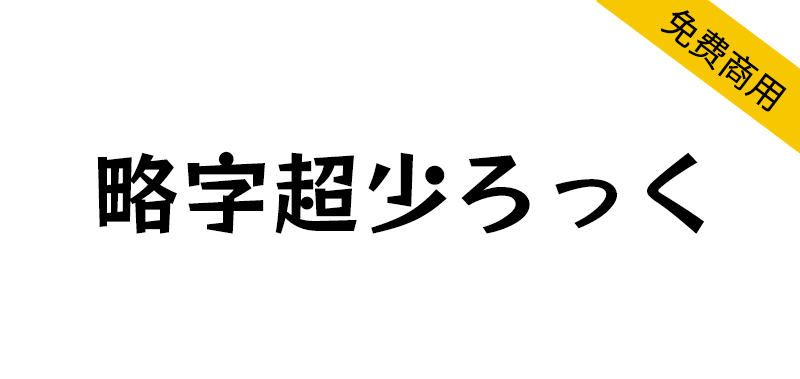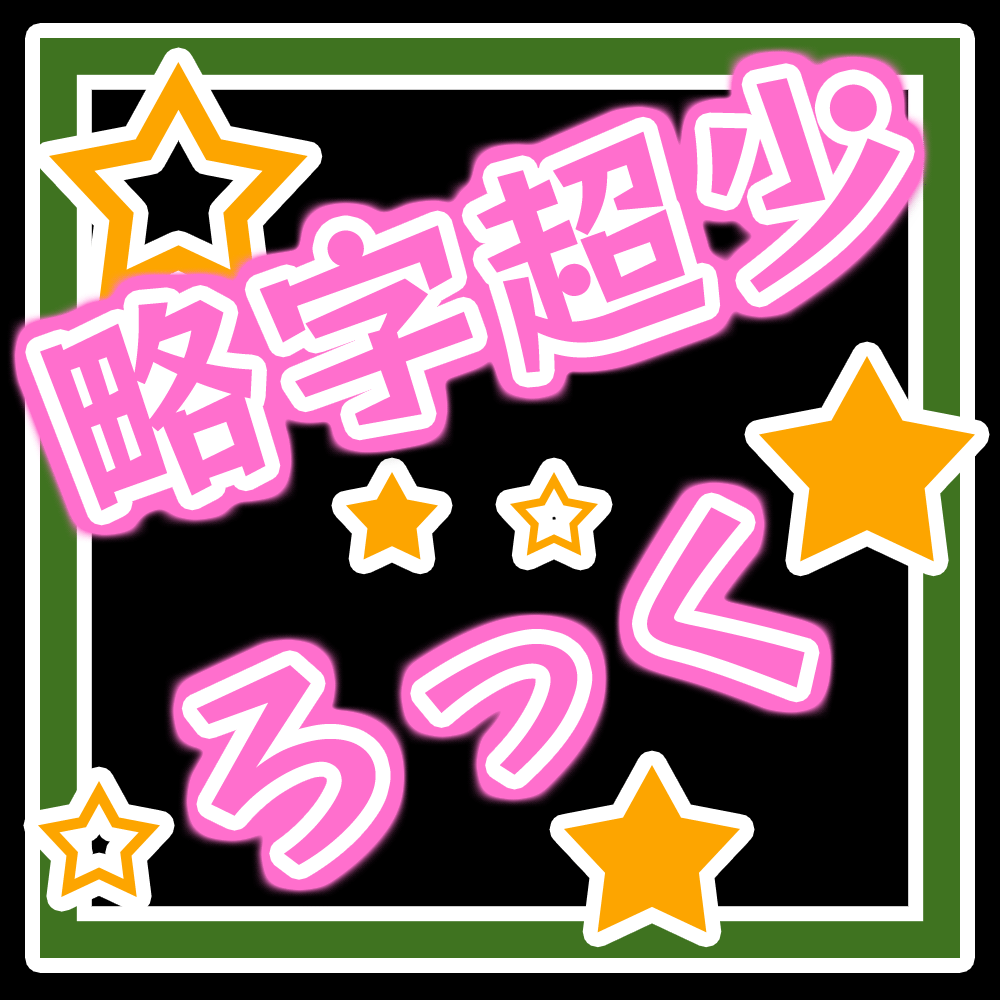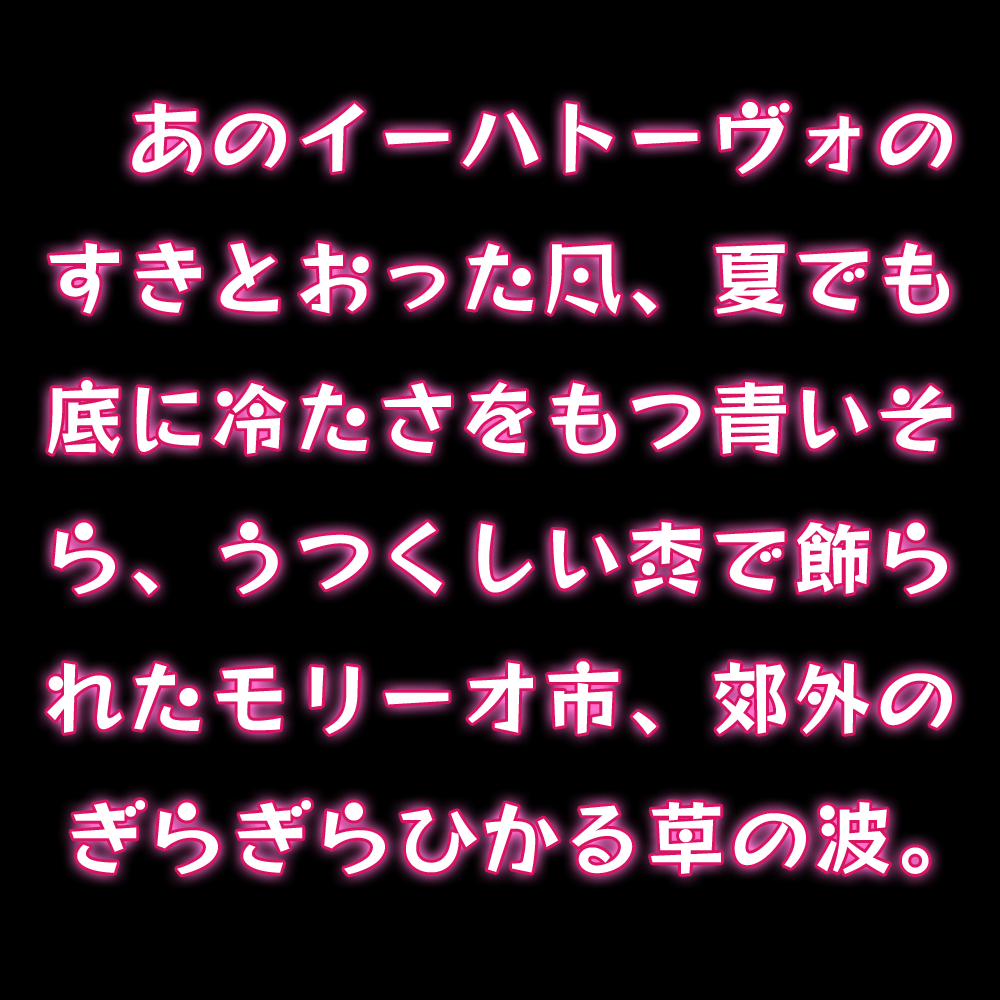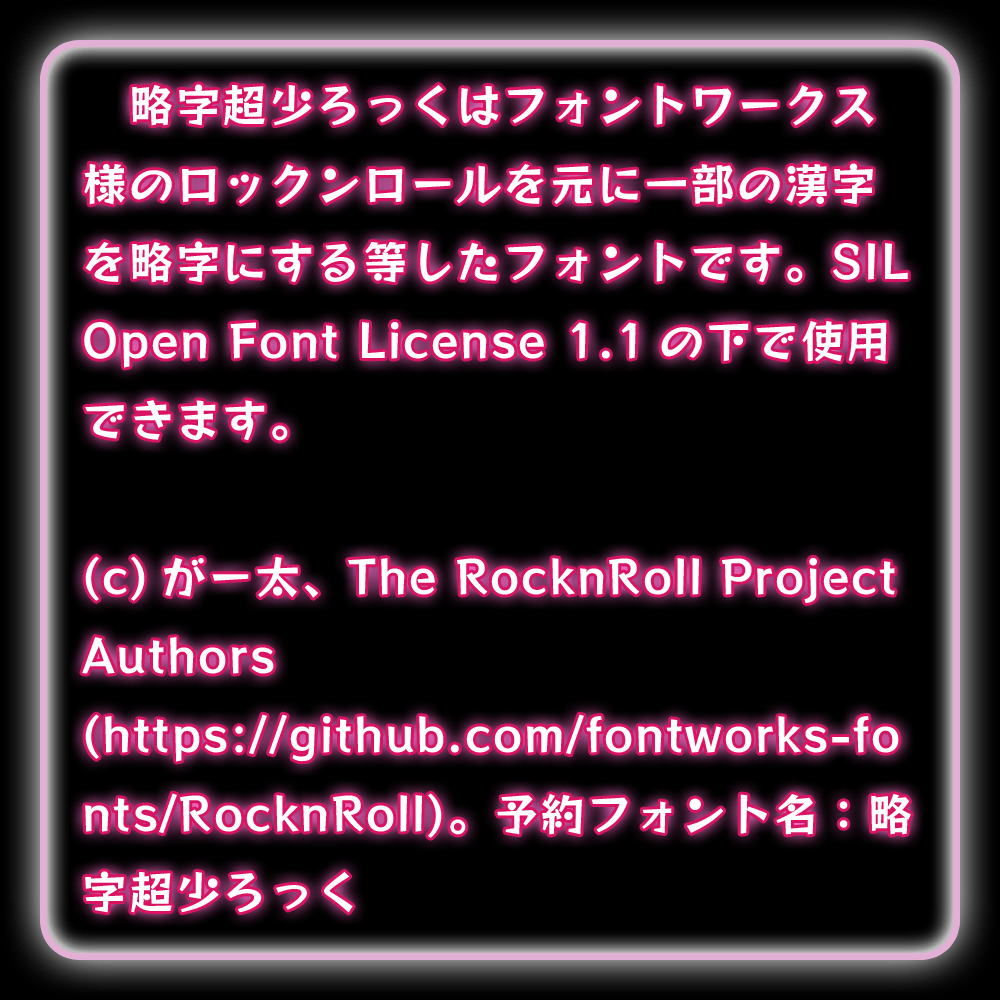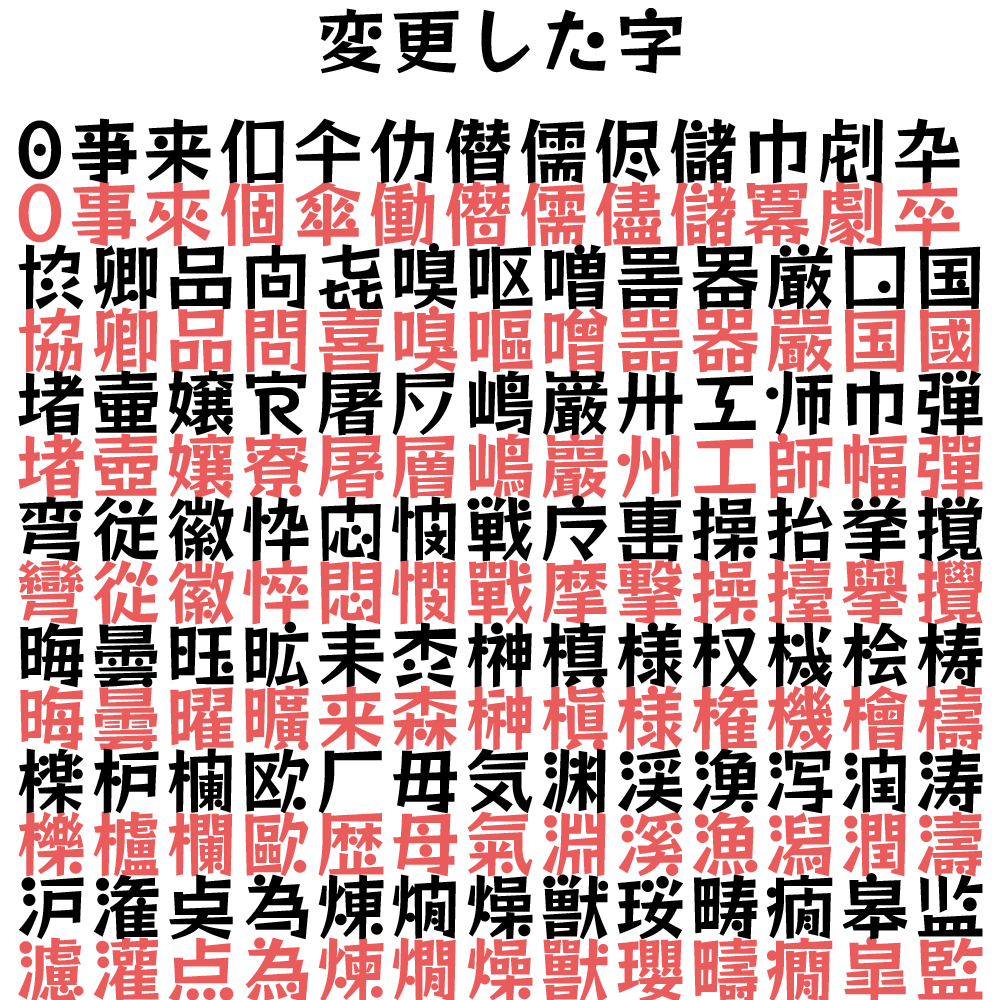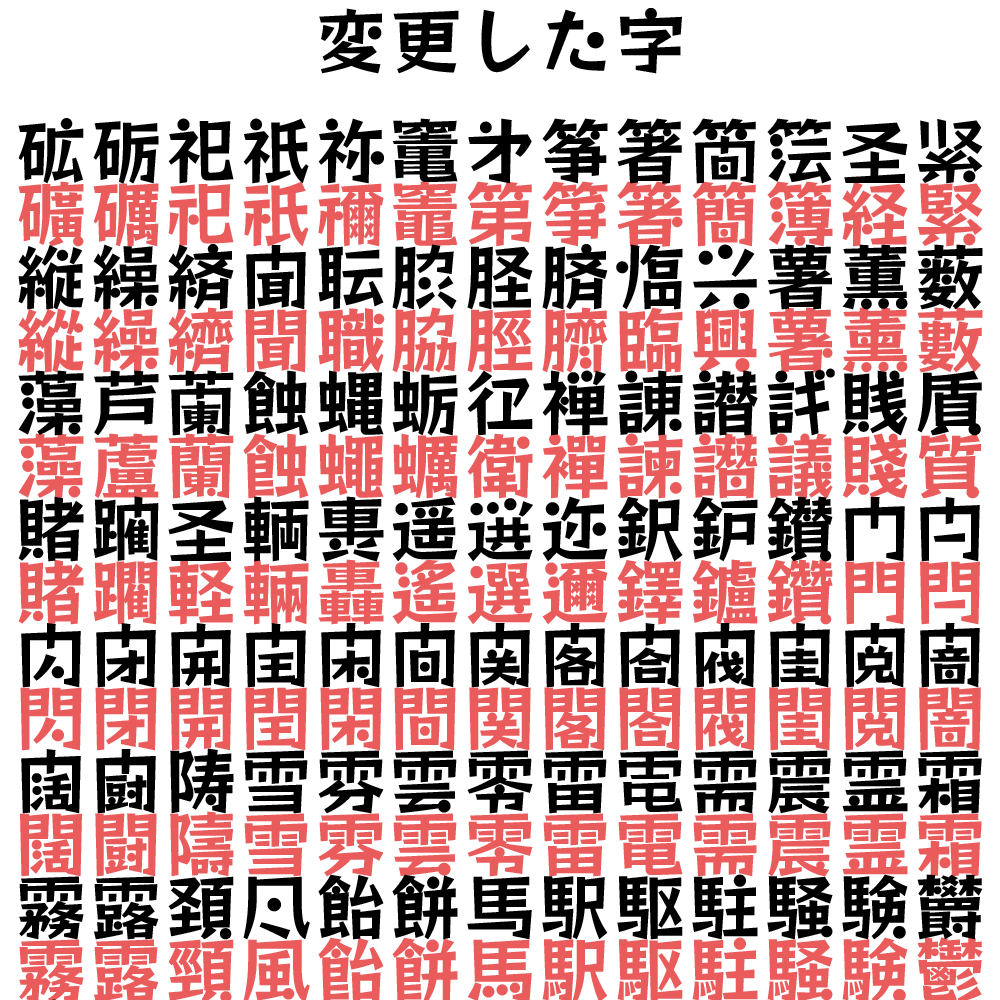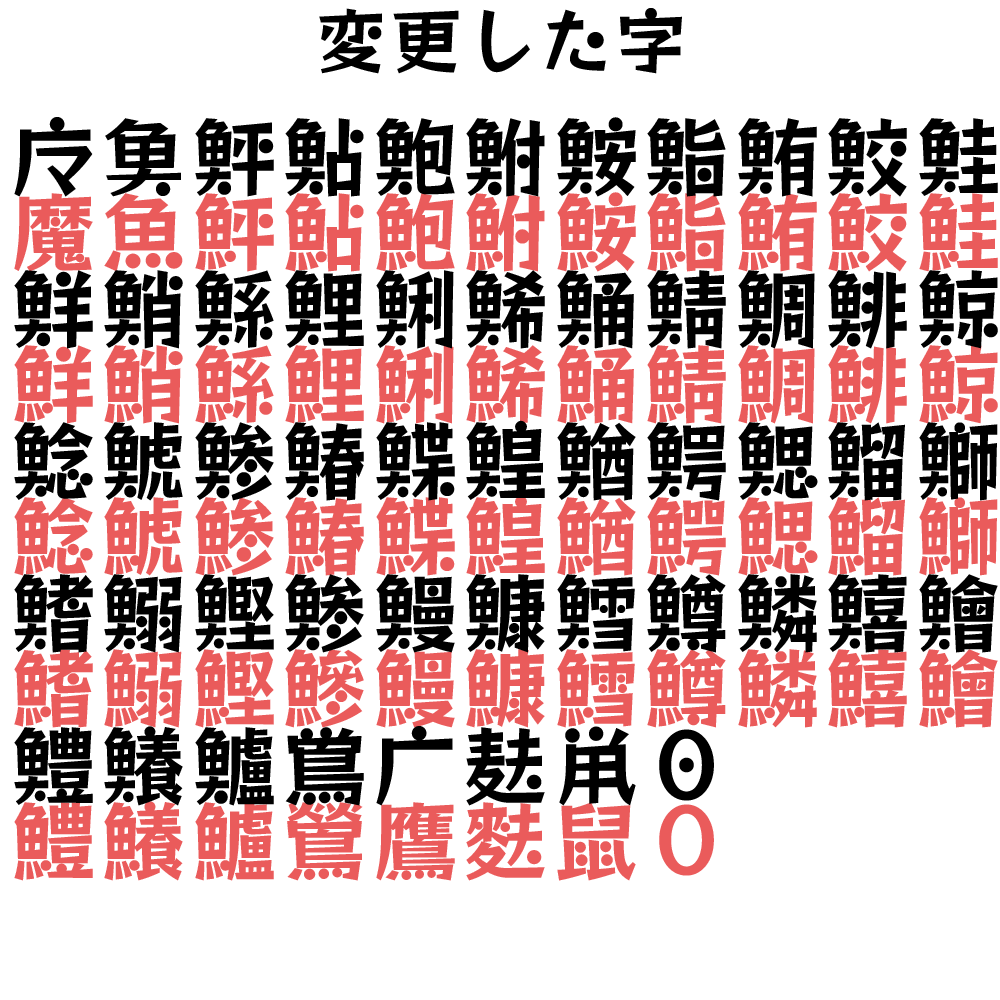
【略字超少ろっく】基于RocknRoll One将一部分汉字缩略
汉字缩略竟能免费商用?揭秘“略字超少ろっく”——这款基于RocknRoll One的创意字体,巧妙压缩部分汉字结构,瞬间提升排版效率!它采用SIL Open Font License 1.1协议,个人企业均可无成本商用,自由安装、分享甚至二次改造(修改后仍需开源)。但注意:禁止单独售卖字体文件或用于违法行为。设计师和内容创作者速取,解锁高效又合规的视觉新方案,点击探索完整使用指南!
【略字超少ろっく】基于RocknRoll One将一部分汉字缩略
略字超少ろっく是以RocknRoll One字体为基础,将一部分汉字缩写的字体。可在SIL Open Font License1.1协议下自由使用。
【略字超少ろっく】基于RocknRoll One将一部分汉字缩略